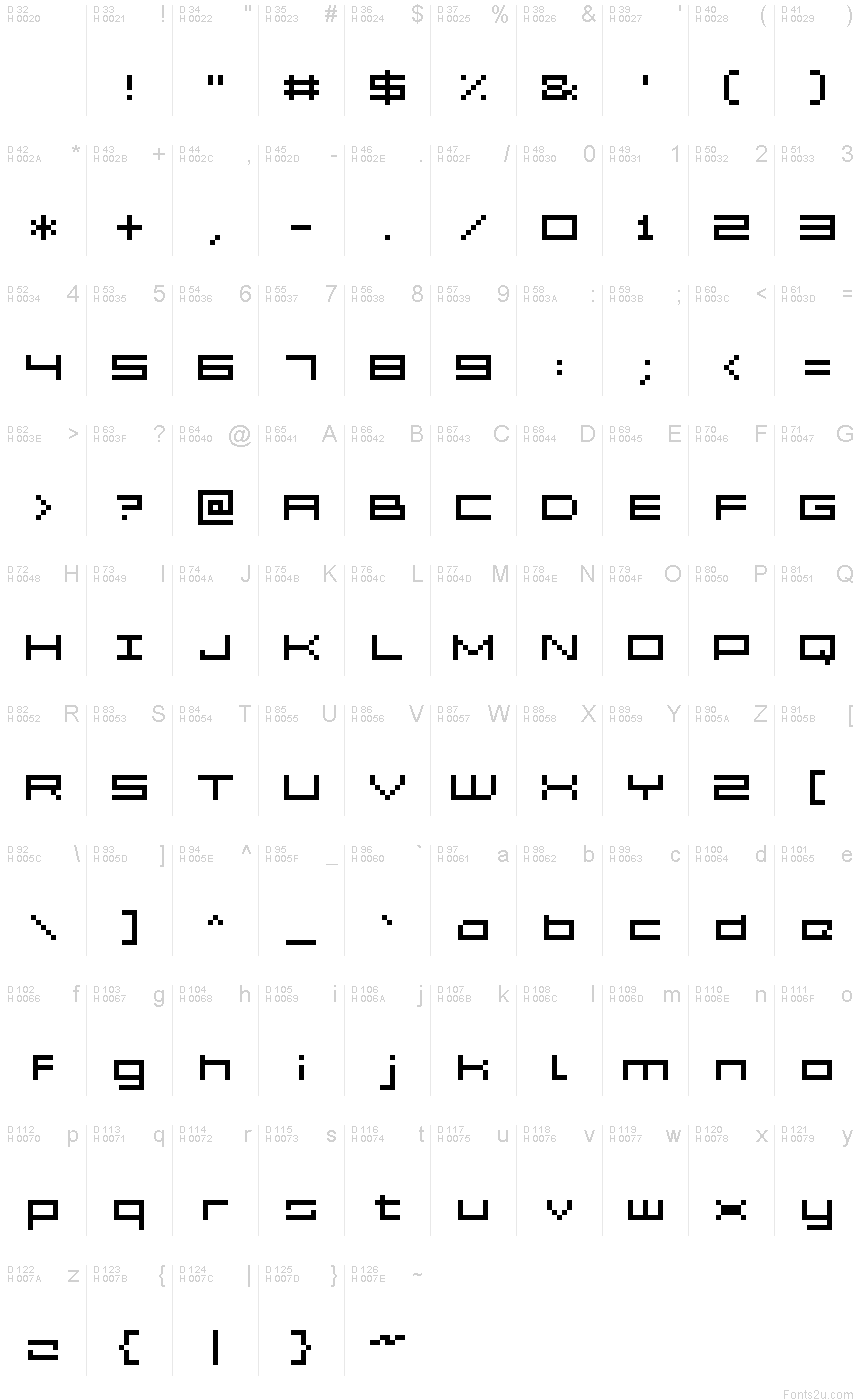
Grixel Acme 5 Wide Xtnd
خط Grixel Acme 5 Wide Xtnd من Greek Pixel Fonts هو خط بكسل نقطي مجاني يقوم بتمديد كل حرف في شكل عريض وضخم دون فقدان الوضوح. بفضل تثبيته داخل شبكة دقيقة، تبدو ضرباته السميكة وزواياه المربعة وكأنها منحوتة مباشرة من شاشة ألعاب الأركيد القديمة، مع الحفاظ على لمسة عصرية ونظيفة. ضمن عائلة Grixel Acme 5، يمنحك هذا الإصدار العريض تأثيراً قوياً بدقة منخفضة، حتى عند العمل بعدد محدود جداً من البكسلات أفقياً.
باستخدام Grixel Acme 5 Wide Xtnd، يمكنك منح واجهات الألعاب (HUD)، ولوحات النتائج، وشاشات البدء القديمة، ومرئيات الديمو، وملصقات السنثويف، وشعارات فن البكسل إيقاعاً أفقياً قوياً يُقرأ بوضوح فوري. هذا الخط المجاني رائع للعناوين الكبيرة، ويمكن دمجه مع خط بكسل أكثر نحافة أو خط أحادي المسافة للنصوص الأساسية للحفاظ على توازن التصميم.